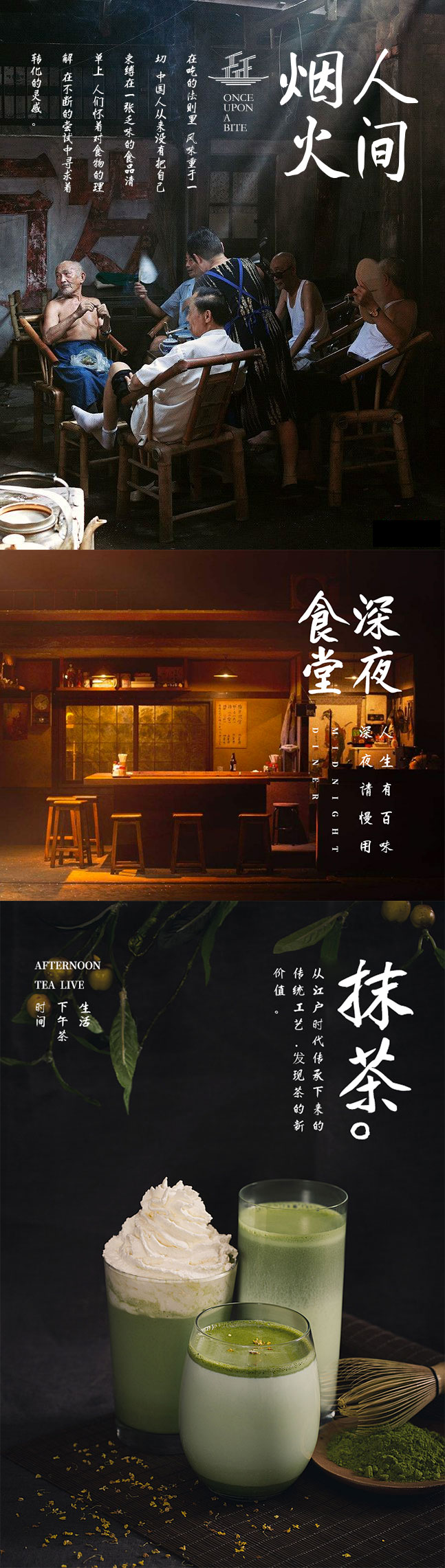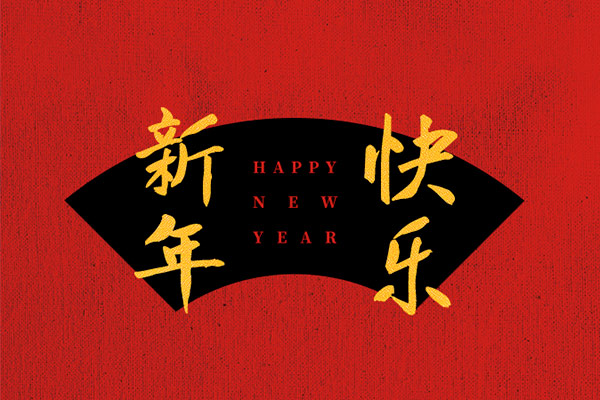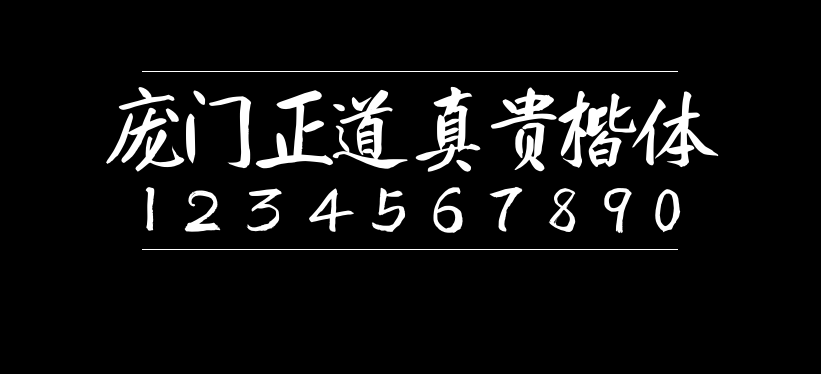
庞门正道真贵楷体
庞门正道真贵楷体是知名设计大V庞门正道(昵称:阿门,真名:)的父亲庞真贵老先生,于76岁高龄历时9个月书写制作而成,适用于中国风等商用画面设计配搭。
以下是作者阿门关于字体来历的介绍:
这篇文章,我的起草,其实是2017年12月,也就是庞门正道标题体的修正版发布之后没多久,我就想到了是否要找一下我的父亲写一个字库,后来大家都知道,之后找的车同学先完成了。
在说这个字体之前,用简单的 文字介绍一下我的父亲。
庞真贵
76岁,古稀之年。
地道农民出身,但是祖父乃一届秀才,也就是我的曾祖父为清朝秀才。
从小好学,可惜当年条件不允许,上了十年学左右,就不得不参加工作。
关于这个,他在我小时候给我讲过一个自己的故事,那时候没有电灯,挑烛夜学,桌面放了一碗水,困了,就用水擦一下眼睛,清醒了继续看书,这个故事那么多年来都激励着我。
80年代,赶上祖国腾飞的大势,和很多广东男子一样,从事了建筑行业,也就是我们熟知的农民工。
也是由于自身的刻苦钻研精神,买了非常多建筑行业的资料自学,从普通农民工经过十几年的努力,工作上作出了让旁人羡慕的成绩。
在这数十年来,他经历了起起落落,唯一不变的,就是坚持着写书法。在我还在老家念书的时期,经常看到他6点多就起来写字,非常勤快,上瘾了一样。如今更是5点多就起来写字了。
很多人说我工作狂,勤奋到不得了,其实比起老爸,我还算是懒惰的。
很多年轻人,做着一份工作,都说下班不想动,太累,想一下老爸当年做的还是苦力活,真正的混泥土移动师(搬砖工),在休息的缝隙,都用棍子和水在砖头上练字,如果你真的热爱,真的不会觉得累。
也是因为这份执着,让他坚持写了六十多年的书法,他今年11月在湛江举办了首个个人书法作品展(草书、行书、楷书),这个在我们整个家族乃至整个镇里,都是第一人,这是我们大家族的光荣。
村口的大石头,上面的字就是老爸字迹,如果是一般人,就写什么一帆风顺了,但是老爸不喜欢庸俗化,想到村里几十年前经常有鹤过来栖息,村头有一棵超大的榕树,所以写下了这4个字:鹤影榕凤。
事情在2017年底,产生了让老爸写一款字体的想法。
2018年初,和他提了这事,老爸非常爽快答应了,因为过去的十几年,几乎都没有开口让他帮忙我做什么事,难得我这次请他帮忙,还是做自己擅长的事,所以他还是很开心的。
他有问我,做这个事情,儿子你可以赚到钱吗?我说没有,这个是免费给大家用的,他有所困惑,这个事情需要忙活小一年,如果不赚钱,我会不会吃亏。
我非常理解的,毕竟养儿一百岁,长忧九十九,他总是担心我在外工作赚不到钱,会吃苦。
我和他说,放心吧,儿子已经不需要再吃苦的了,这个字体一来是给大家免费用,二来也是给你那么多年的书法生涯做一个阶段性成果,永远都会有人看得到你写的字的。
出于对商用性质的考虑,老爸最擅长的草书,需要放弃,行书也不适合,最后选择了楷书作为这次字体的方向。
2018年夏天的照片,那时候已经开始根据字库的字开始试写了。
好事多磨,一套常规字库,6600字,这个工作量对于我们年轻人,都不轻松,何况是一个古稀之年的老人家,因为我不能在老家看着,写完了给我寄过来,一看,楷书还是偏草了一些,不适合,然后和他说需要重写,这个像极了甲方爸爸让我重做一样,我是要崩溃的,但是老爸还是欣然答应。
断断续续,又过了3个月,第二版发过来了。
太细了,粗点的字体才用起来方便,太细的作为标题力度不足。
这,就是商业与艺术的冲突了,就如一些书法家喜欢喷商业书法体各种问题,其实商业书法,有限考虑是商用的便捷性,而不是艺术性。
所以,我又安排他重写了。是的,我都不好意思再说改了,但是为了字体的价值最大化,必须重写。
这次先写了一百几十字,然后微调,终于,调到了我觉得OK的状态。
再次开始全部6600再写一遍。
这个时候,已经来到了2019年初了。
字体已经制作完,等待测试。
字体命名就用他老人家的名字吧,庞真贵。
所以这款字体就叫:庞门正道真贵楷体!
庞门正道真贵楷体为简体字形,已覆盖常用的中文简体汉字(约6600个汉字),简体基本不存在缺字的现象,繁体则支持较少。